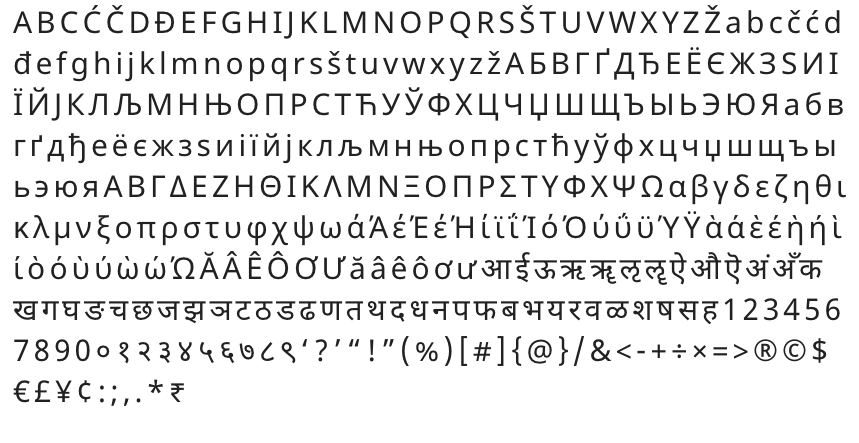
Google ha creado noto, una nueva tipografía universal que se puede usar independientemente del idioma del usuario, los caracteres que utilice o los símbolos que quiera escribir.
De esta forma Google quiere evitar el cuadrado en blanco que aparece cuando tipografías populares como Times New Roman o Arial no son capaces de leer ni de expresar ciertos símbolos.
El proyecto se ha estado gestando durante los últimos 5 años y con él se quiere eliminar cualquier barrera a la comunicación.
Noto es una tipografía de código abierto capaz de funcionar en 800 lenguas y que incluye 110.000 caracteres. Su nacimiento viene de la necesidad de contar con sistemas Android y Chrome OS más competentes, dada su amplia expansión internacional.